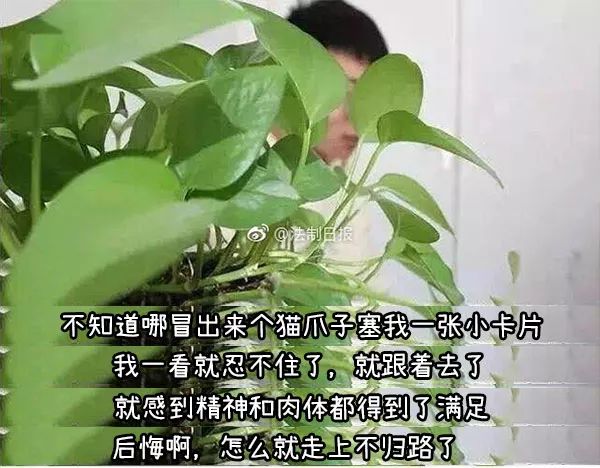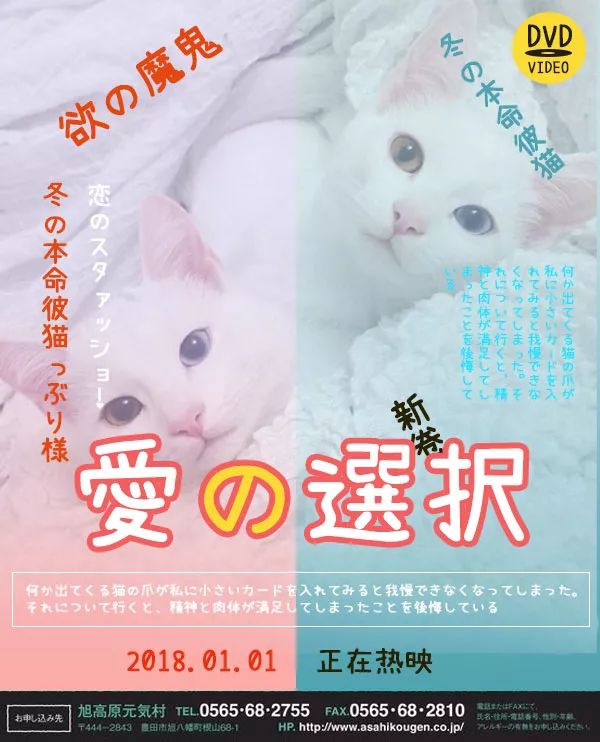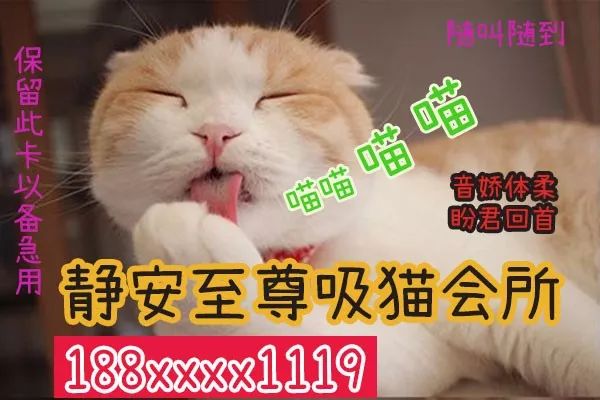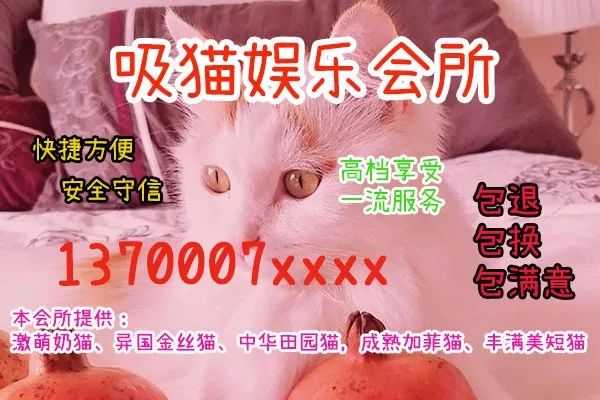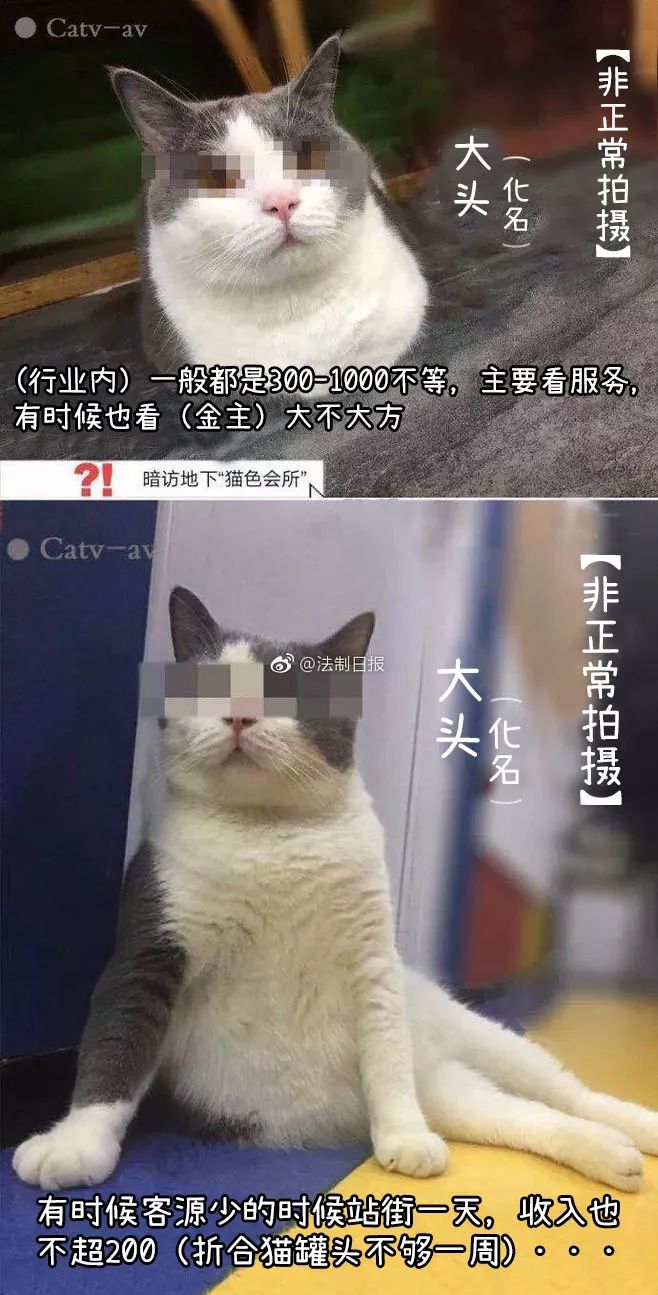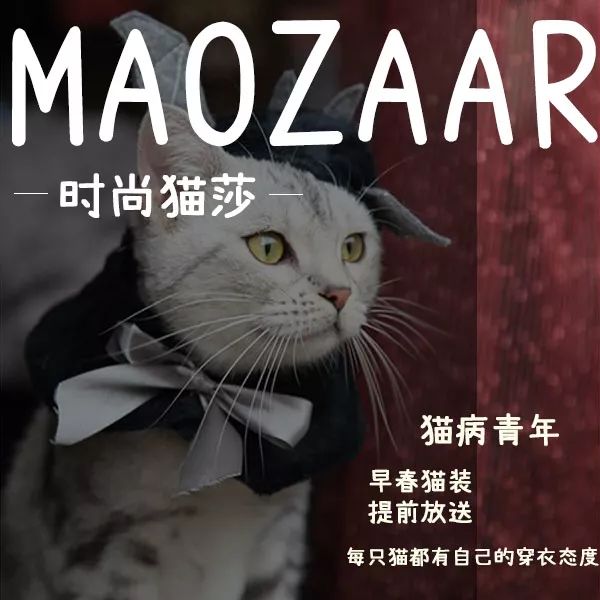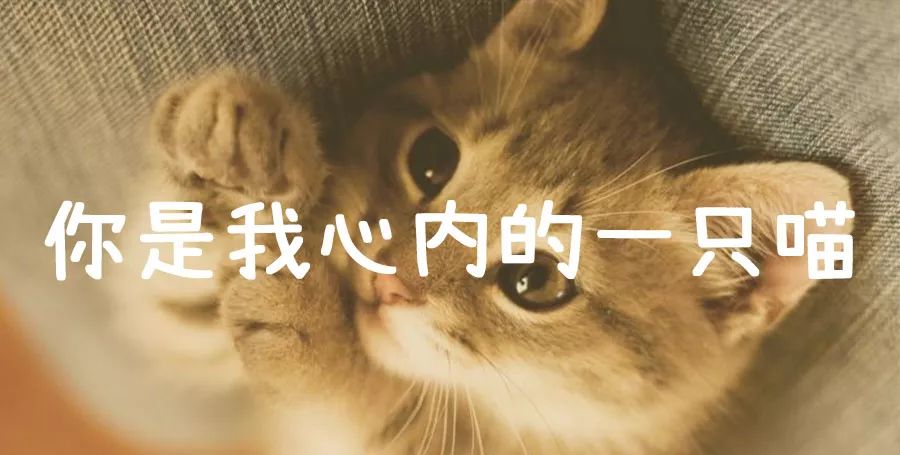
这里有只猫你要不要吸一吸
吸猫作为城市空巢青年的成瘾行为
与摄影器材、毒品并称社会三大毒瘤
猫咪看似温柔可爱
一旦你开始接触、“吸拾”
会时时刻刻影响你的工作与生活
它用柔软的身躯、可爱的后脑和温暖的肚皮
反复诱惑你
不管你拥有多么惊人的意志力
一旦“吸拾”就会不能自拔
为了满足社会上这些吸猫成瘾的
“猫病青年”
一些不法份子借机利用猫来牟取暴利
为了获取更高额的暴利还出版了
大量猫咪影视、写真、海报等
将吸猫线上产业不断扩大
但苦于线上资源能看不能吸
“猫病青年”对吸猫的需求更是越来越大
从而促使部分人铤而走险
做起了线下吸猫产业
更可气的是这些不法份子为了省钱
海报宣传所有用字都是
濑户字体
字体可爱不说更加助长吸猫图的诱惑力
面对这种不良风气
小编忠心劝慰大家
珍爱生命,远离吸猫!!!